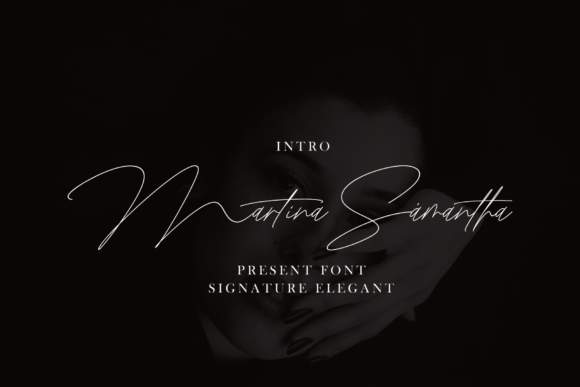
Martina Samantha
適切なデザイン要素を見つけるのは難しい場合がありますが、Martina Samanthaは作品を即座に引き立てる優れたコレクションを提供します。
POD(オンデマンド印刷)製品、結婚式の招待状、またはソーシャルメディアのグラフィックを作成している場合でも、Martina Samanthaは理想的です。